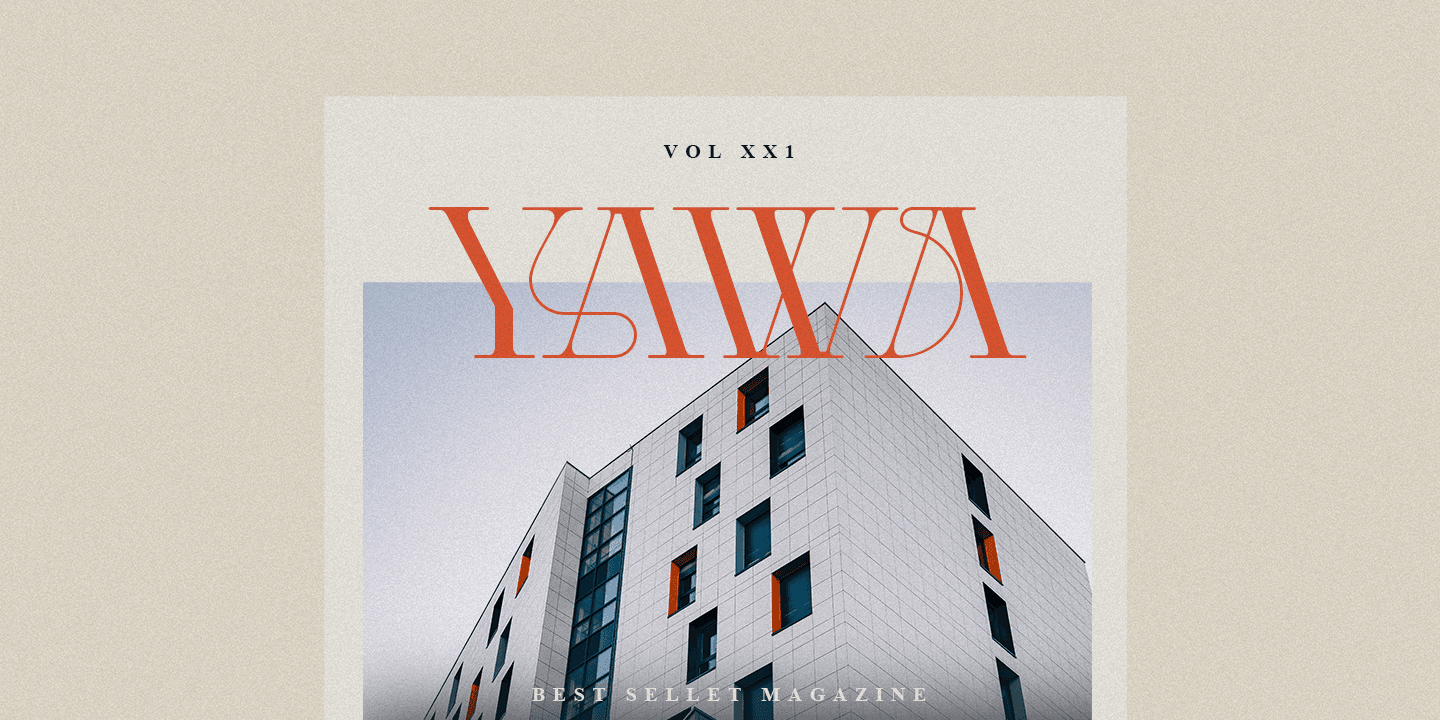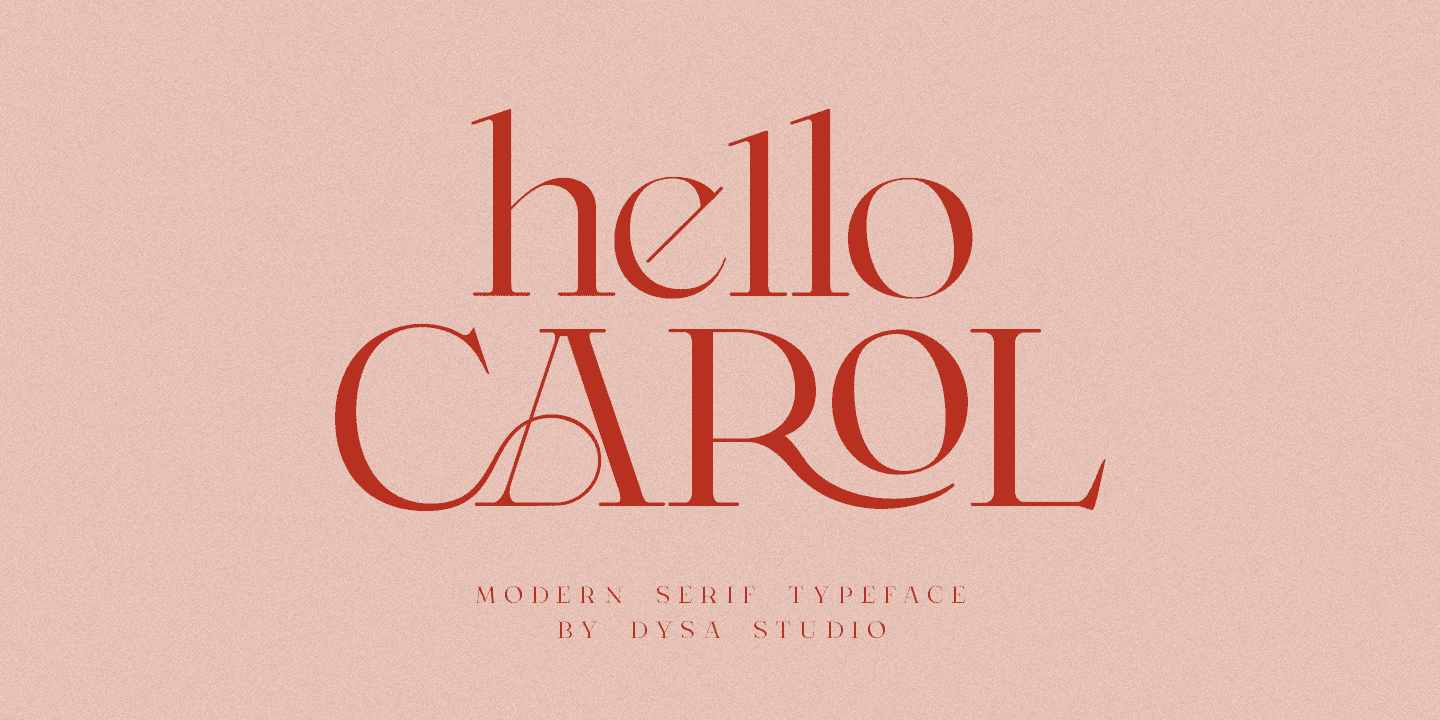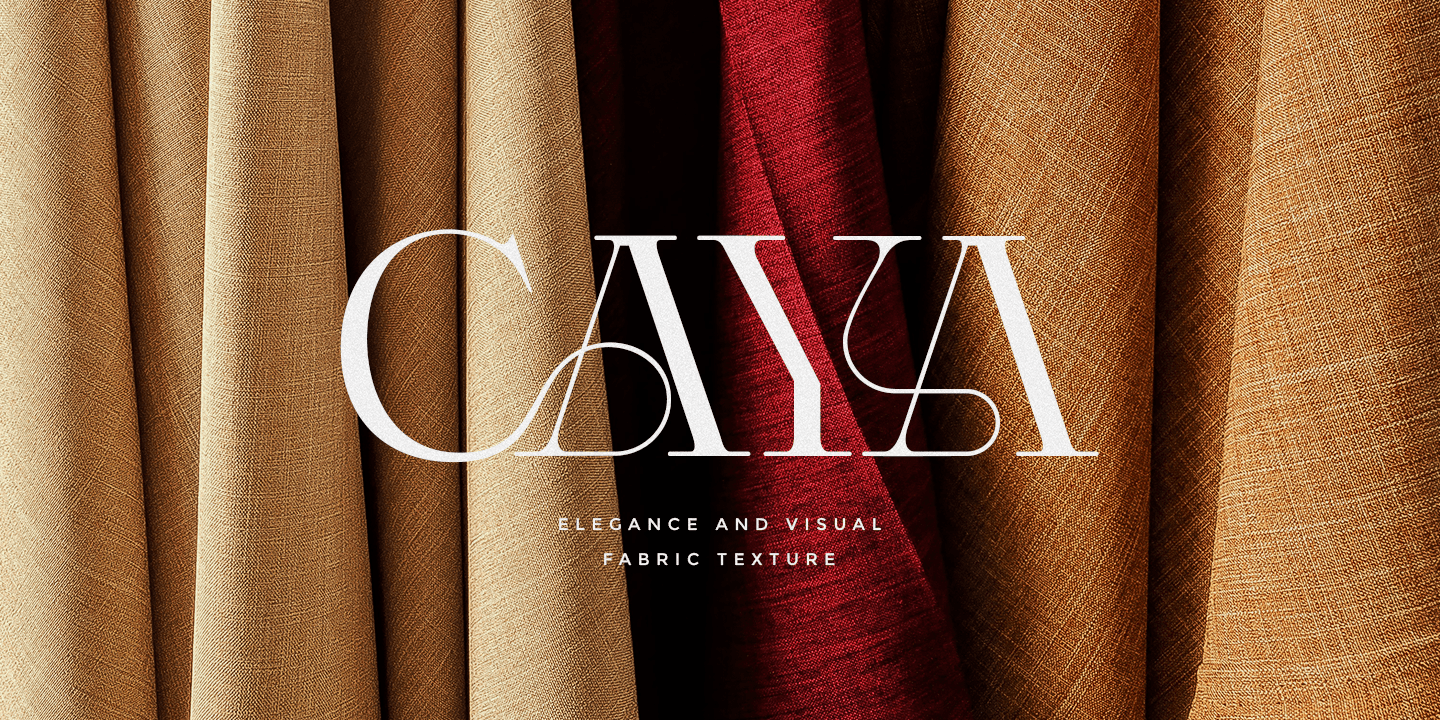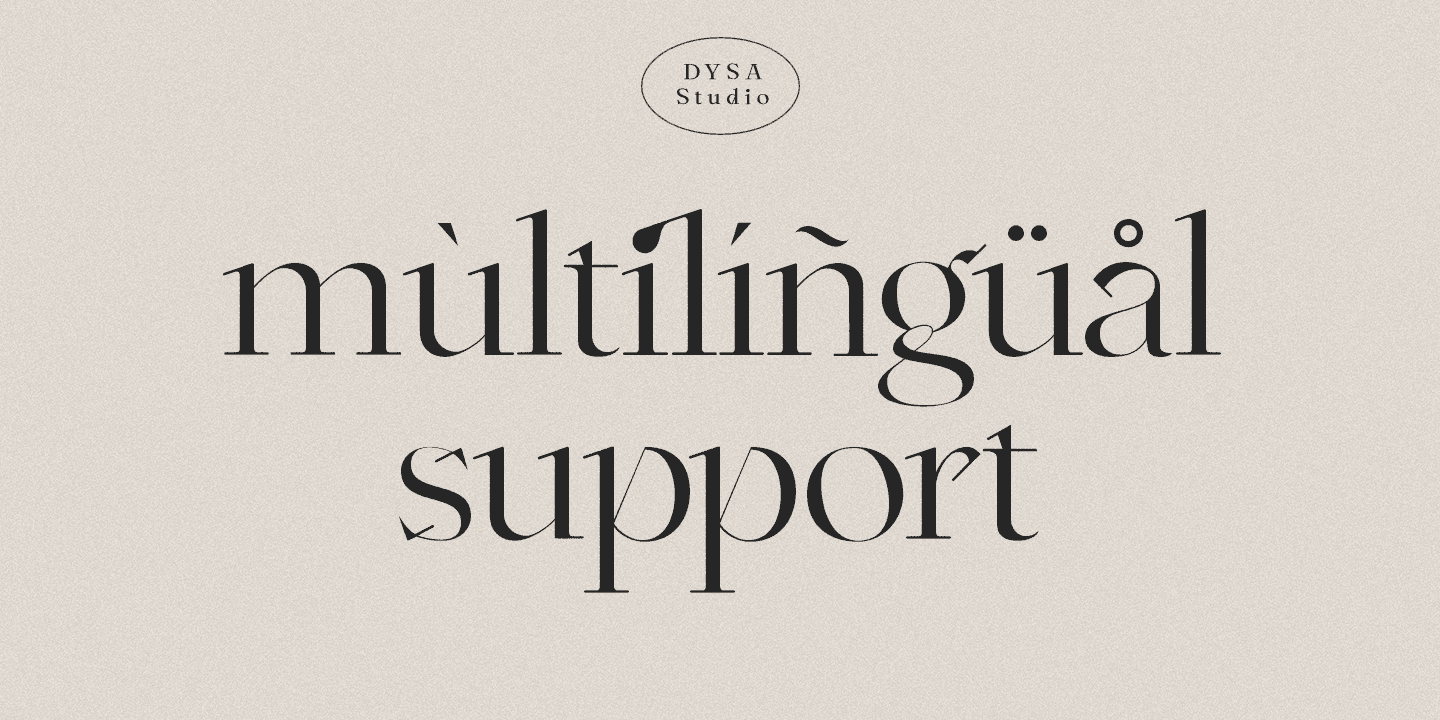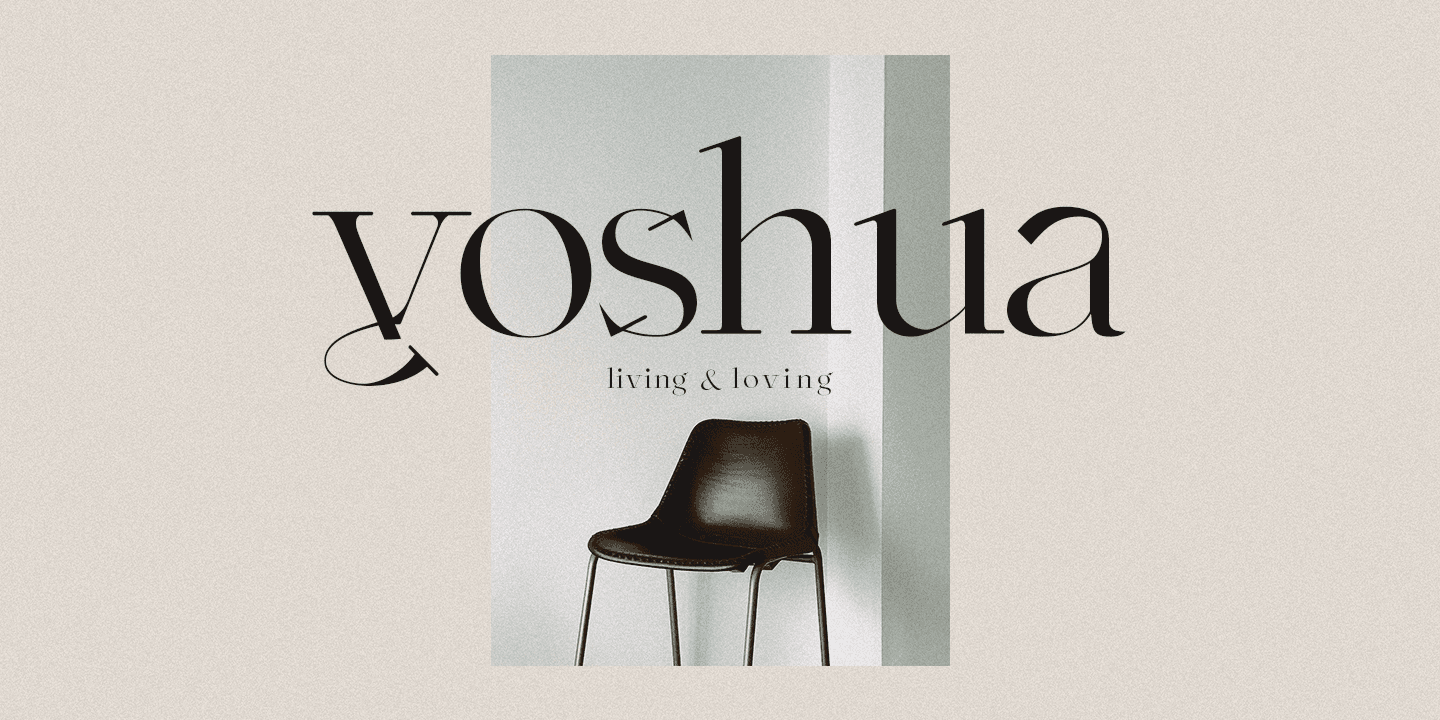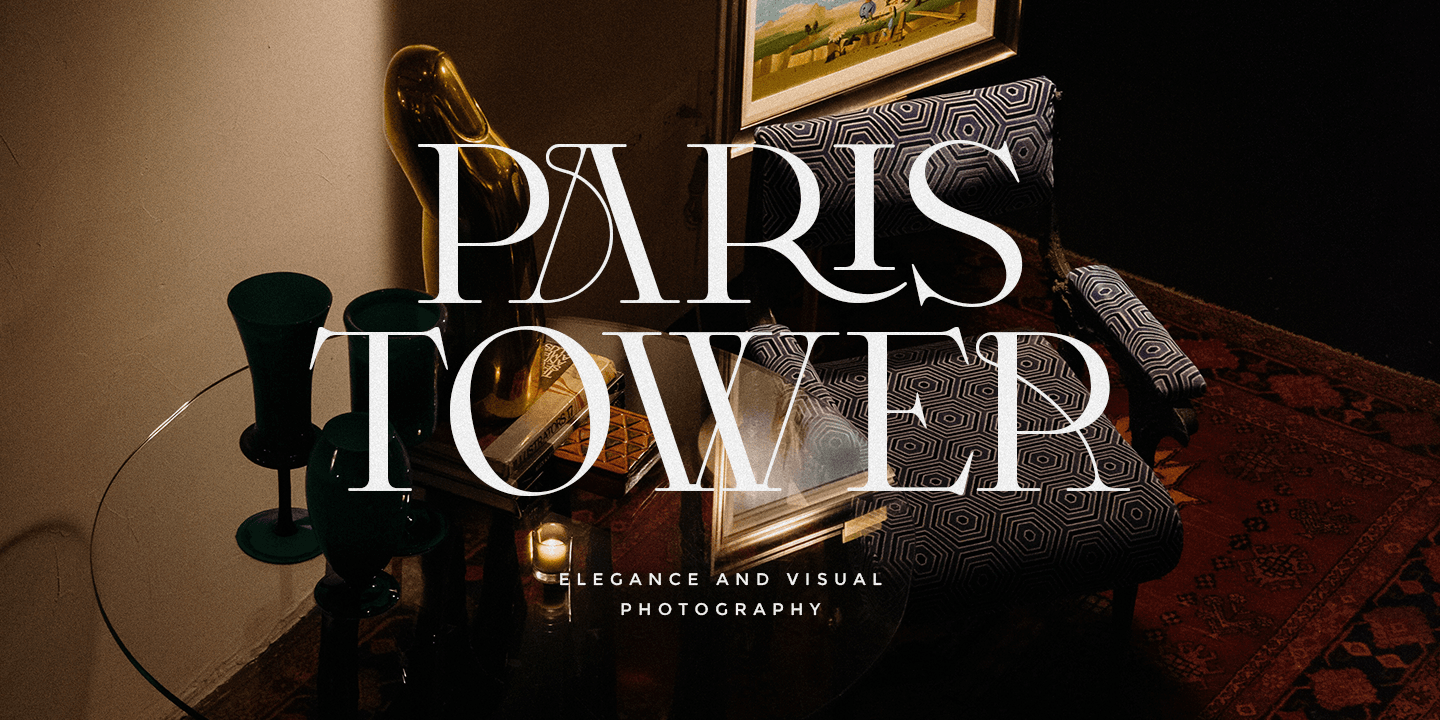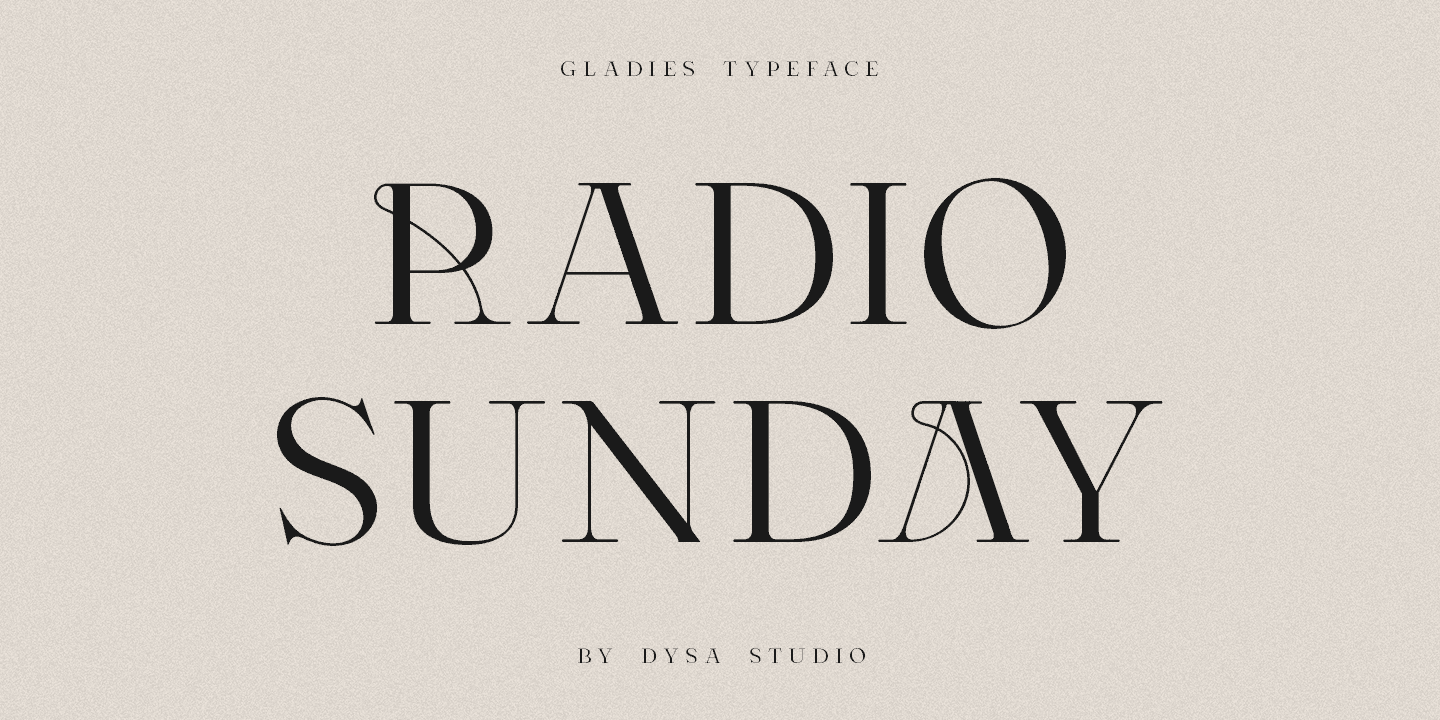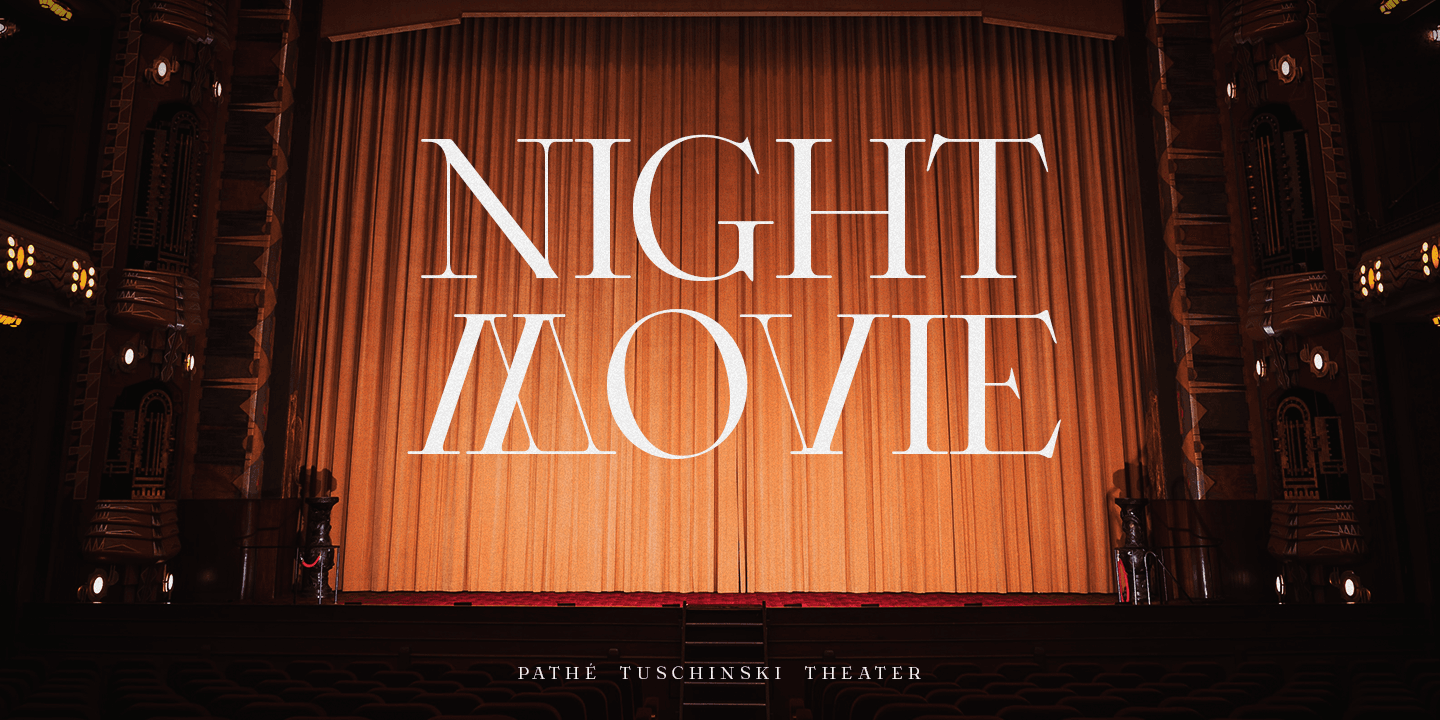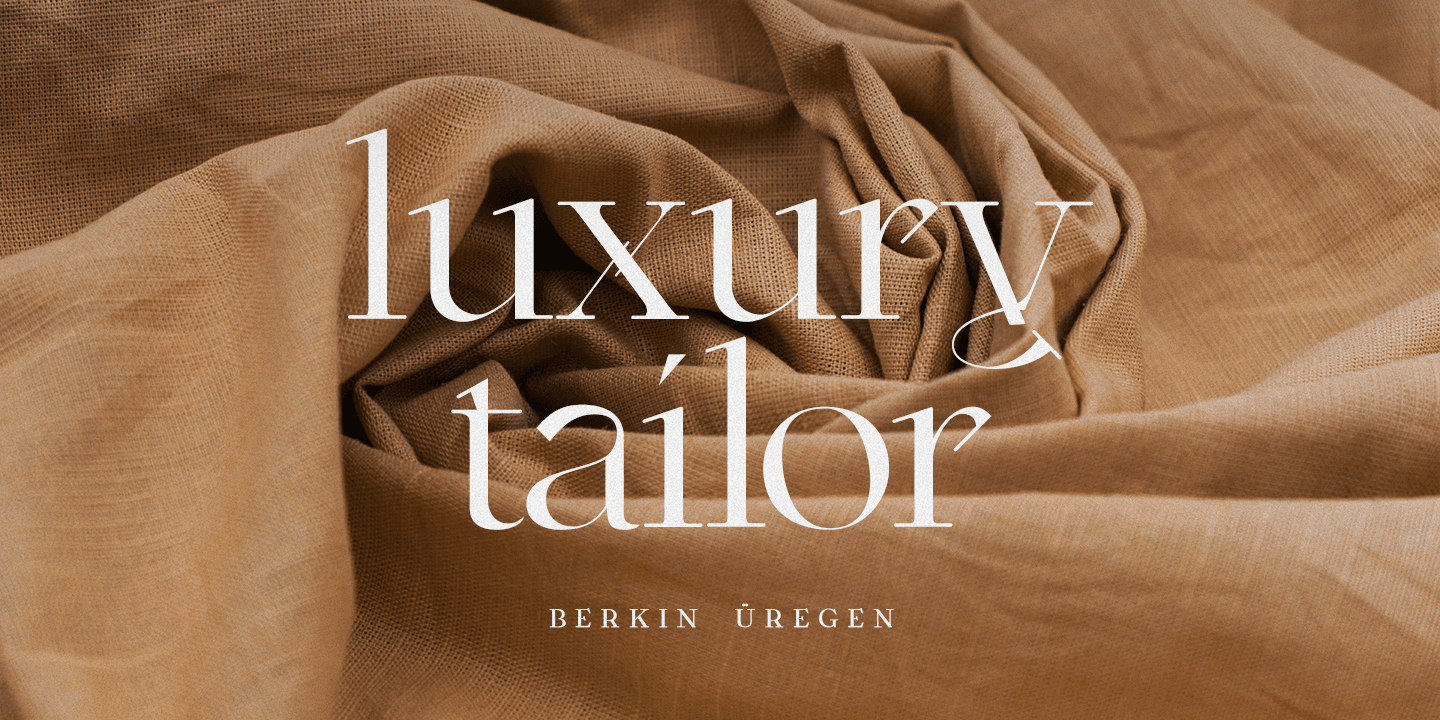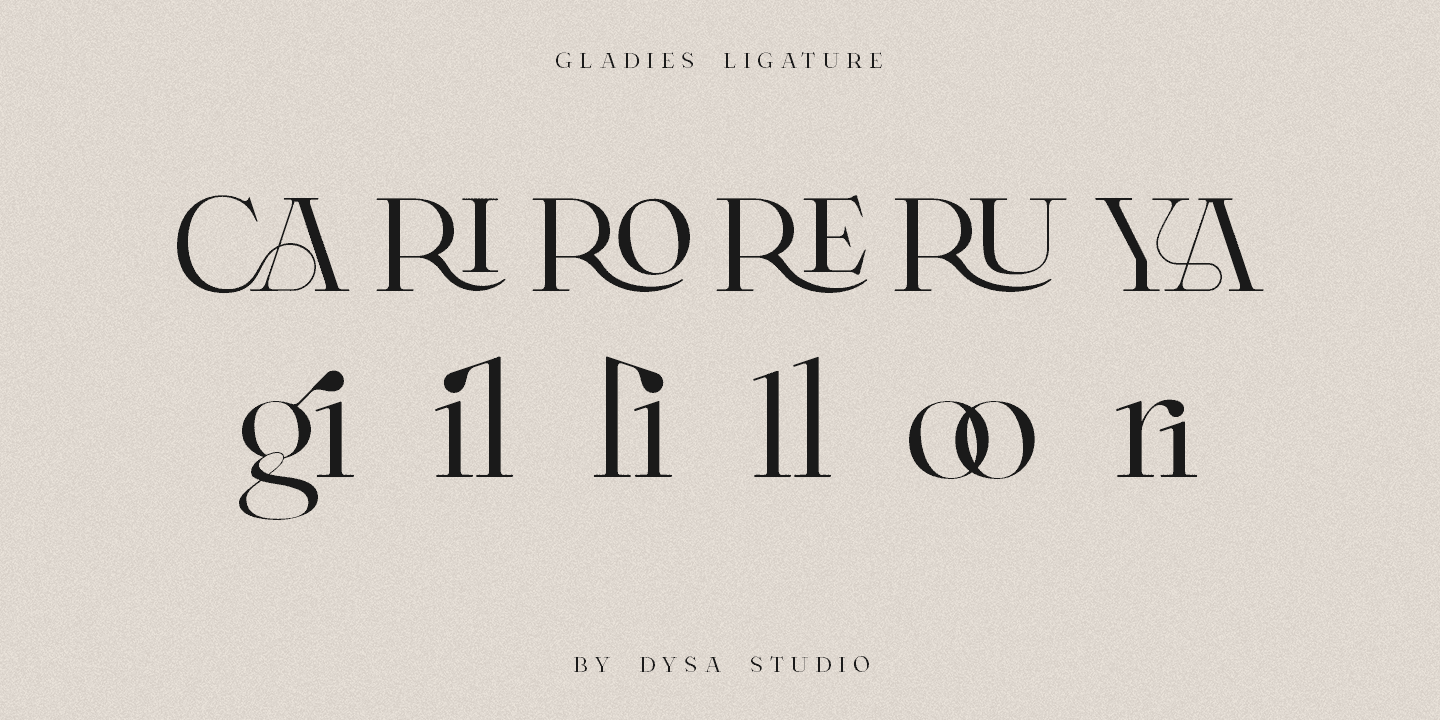
Gladies là một font chữ Modern Serif Typeface mới. Gladies Font này hoàn hảo cho dự án xây dựng thương hiệu với phong cách hiện đại, tuyệt vời cho doanh nghiệp của bạn. Gladies với các thiết kế tỉ mỉ mang đến một phong cách ấn tượng và mới lạ
Gladies là sự lựa chọn hoàn hảo cho những người đang tìm kiếm một font chữ với phong cách thiết kế đẹp, hiện đại, tối giản, thanh lịch. Thích hợp cho hầu hết mọi thiết kế đồ họa như logo, vật liệu xây dựng thương hiệu, danh thiếp, thẻ quà tặng, áo thun, bìa, hình thu nhỏ, in ấn, áp phích, nhiếp ảnh, trích dẫn. Vv